Fonte
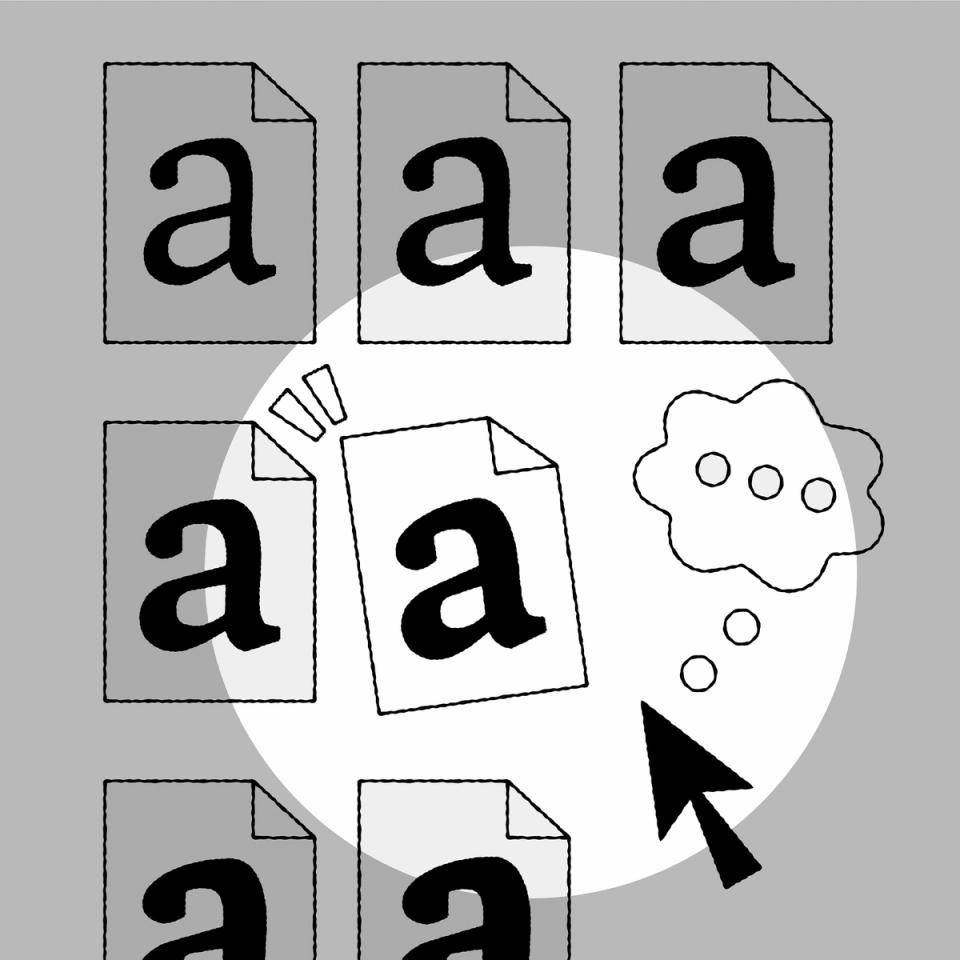
Depuis l’ère de l’impression au plomb, une fonte était un ensemble de caractères en plomb d’un style spécifique d’une police de caractères. Par exemple, le Times New Roman en 10pts, Times New Roman Gras en 16pts, et Times New Roman Gras Italique en 16pts étaient trois fontes distinctes de la police Times New Roman.
Le mot fonte (on dit même « font » en anglais) vient du verbe français fondre, car les caractères étaient alors fabriqués en faisant fondre un alliage composé de plomb qui était versé dans des matrices pour les produire en série.
À l’ère numérique, une fonte est un fichier unique d’un caractère avec un ou plusieurs styles. Avec les fontes statiques, un fichier correspond à un seul style. Avec les fontes variables, un seul fichier peut contenir de nombreux styles grâce à des interpolations.
Par exemple :
• Helvetica Neue Light (HelveticaNeue-Light.otf) et Helvetica Neue Light Italic (HelveticaNeue-LightItalic.otf) sont deux fontes statiques indépendantes.
• Helvetica VAR HelveticaVAR.ttf et Helvetica VAR Italic HelveticaVAR-Italic.ttf sont des fontes variables, chacune comportant un ensemble de styles (Light, Regular, Bold, etc.).